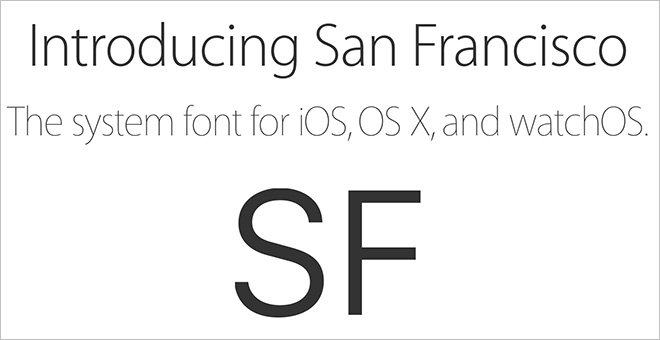
วันนี้ Apple ได้เปิดให้นักพัฒนาได้ดาวน์โหลดฟอนต์ระบบใหม่ ‘San Francisco’ ที่สร้างขึ้นโดย Apple สำหรับนำไปใช้งานกับ iOS 9, OS X El Capitan และ watchOS 2 หรือระบบปฏิบัติการของ Apple Watch นั่นเองครับ
ฟอนต์ San Francisco ถูกสร้างขึ้นครั้งแรกในปี 2014 โดยบริษัท Apple และถูกนำมาใช้กับ Apple Watch โดยฟอนต์ตัวนี้ถูกออกแบบมาให้มีความชัดเจนและอ่านง่ายมากที่สุด โดยในปีนี้ฟอนท์ San Francisco จะถูกนำมาแทนที่ฟอนท์ Helvetica บนทุกระบบปฏิบัติการณ์ ได้แก่ iOS, OS X และ watchOS